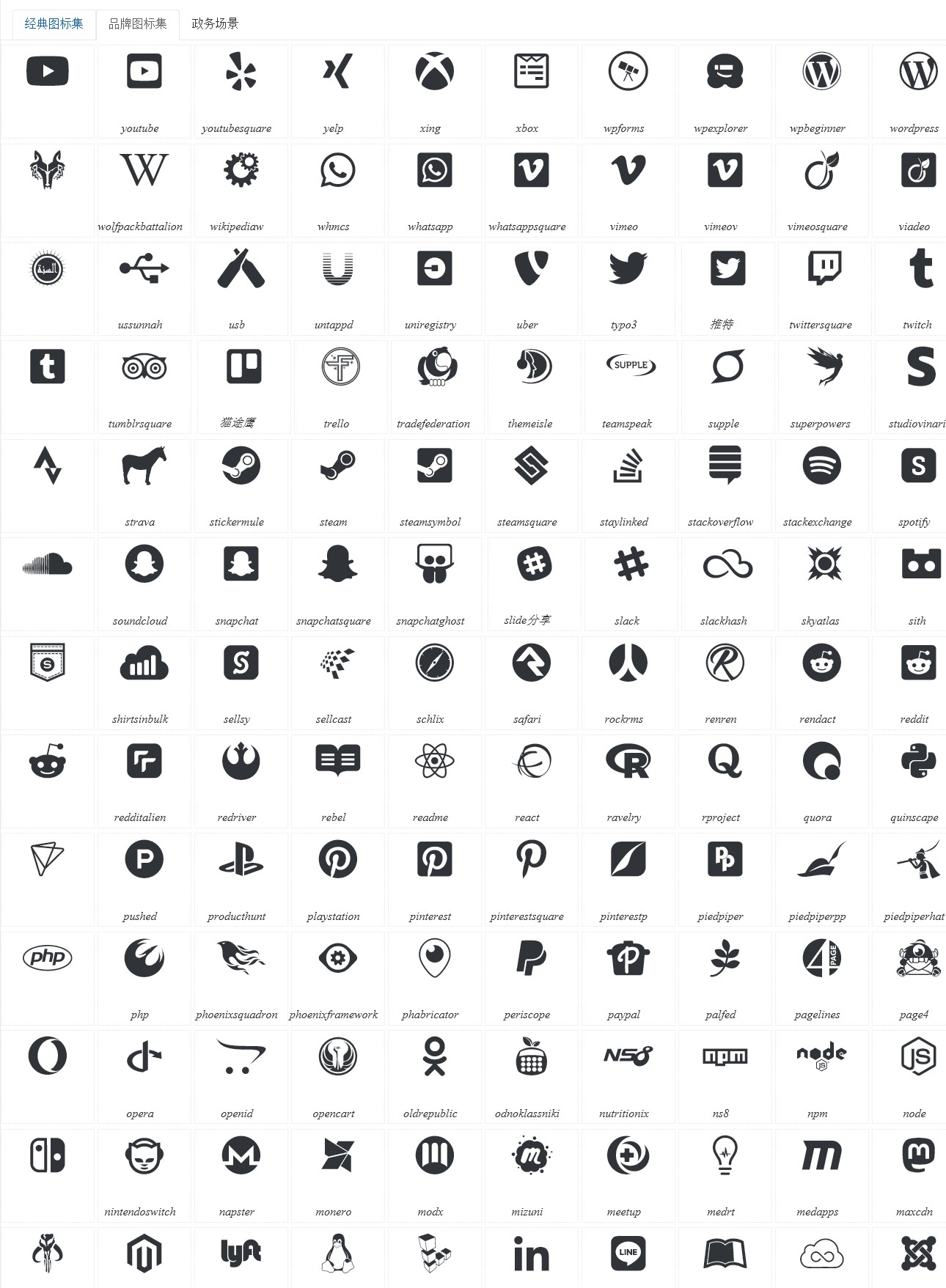
逐浪矢量全真图标
字体名称: 逐浪矢量全真图标
逐浪矢量全真图标体
一个专为中国开发者而生的跨平台图标网站,保证有你所需要的图标,凝聚国际流行风格,如微信,微博,QQ和各种类型的箭头,以及基本的图标如电话、设置、搜索等等,免费开放提供给广大用户使用,欢迎大家使用。
zico基于逐浪图标的元素,力求改变这一目标!
中国技术不能受制于人,文化也同样不应受制于人。
我们的图标集特色:
1、覆盖主流图标集
2、有中国元素
3、更好的使用
本款“逐浪矢量全真图标”是一款书写很新颖的字体,字体大方,适合各种设计作品使用!欢迎下载!